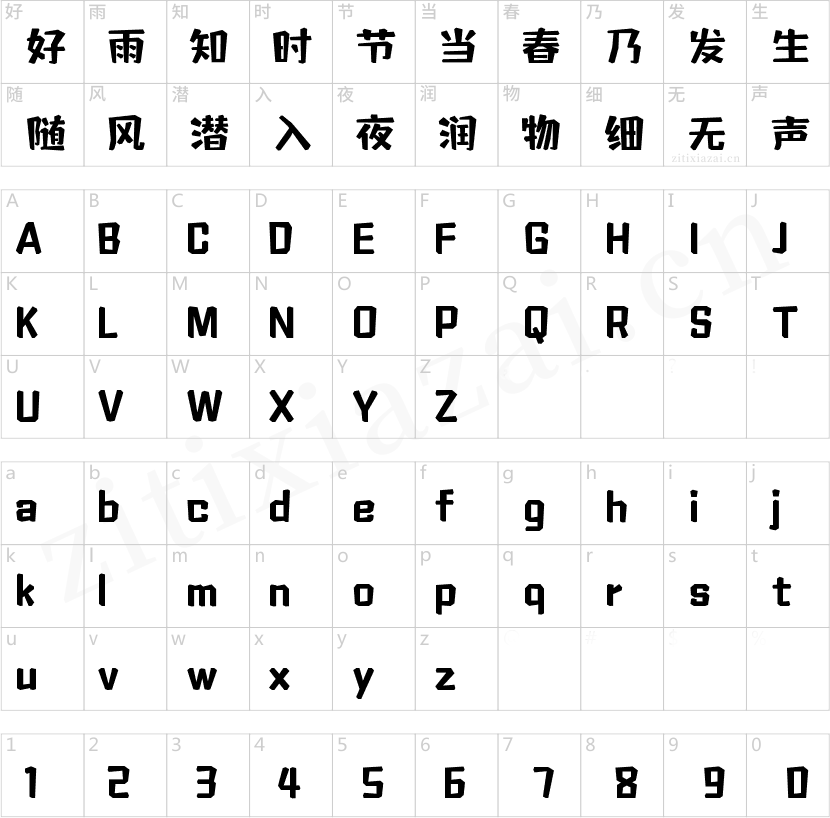
壹心木头人
壹心木头人,这款字体结构工整、笔画清晰,兼顾美观与易读性,适用于标题、正文、海报、包装、LOGO 等多种场景。字形优雅稳定,风格百搭耐看,适配日常排版与创意设计,让文字呈现更舒适、更具质感。壹心木头人一笔一画,皆是细节,以均衡的比例、流畅的线条打造舒适视觉体验,字形端正大气,风格简约现代。无论是商业设计、品牌宣传还是日常排版,都能轻松驾驭,让文字更有格调与力量。壹心木头人字体下载。